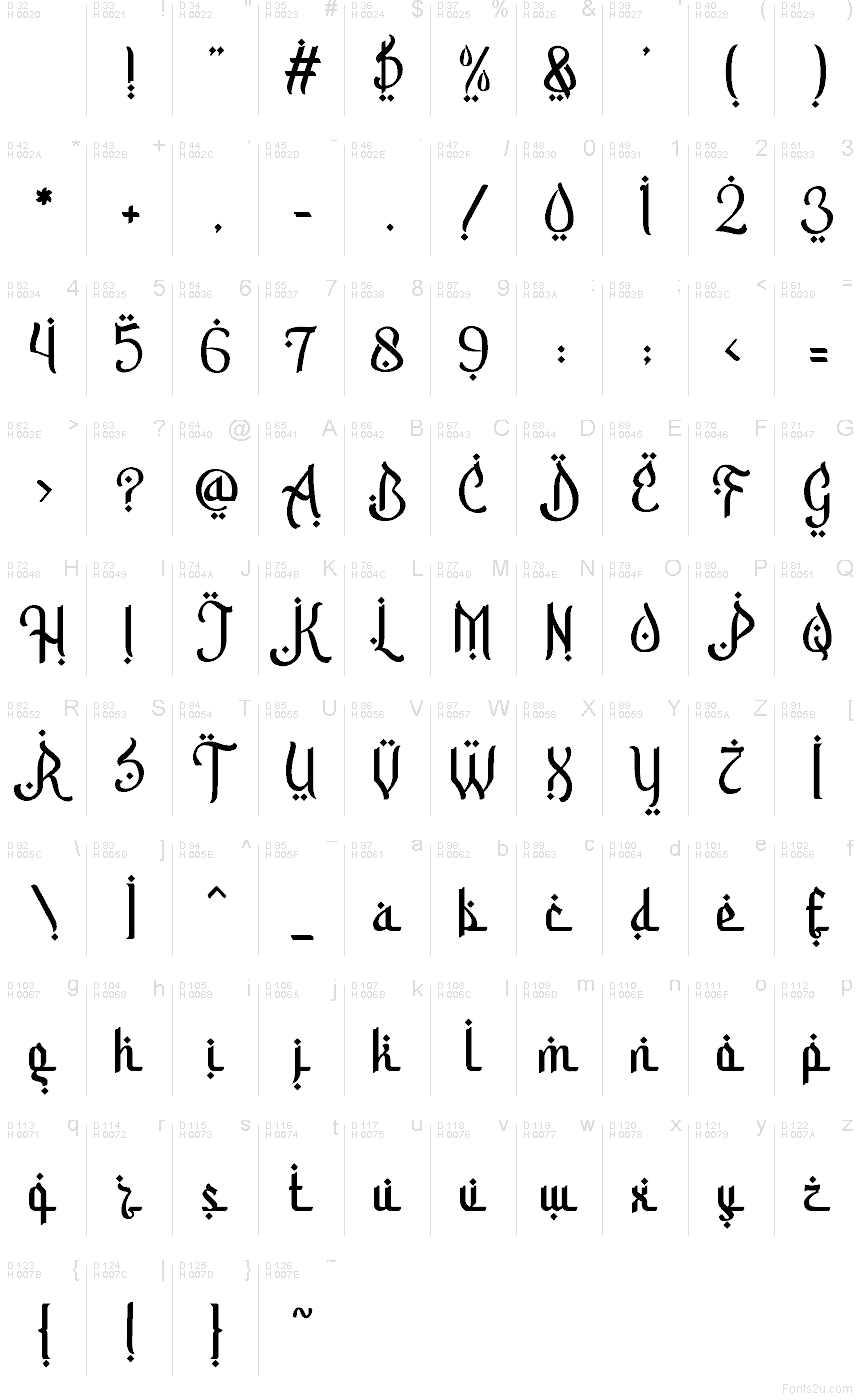
Majidi Mirage Three
Majidi Mirage Three od Putracetol Studio je arabské display písmo, ktoré tvoria vysoké vertikálne ťahy, ostré krivky a pravidelný vzor diamantových bodiek – tie pôsobia ako súčasť konštrukcie, nie ako dekorácia. Tento rytmus dodáva písmenám slávnostný, kaligrafický nádych, zatiaľ čo široké spodné krivky udržiavajú celkový vzhľad pevne na zemi.
Plagáty, titulky, obaly kníh, branding a grafika pre podujatia môžu využiť túto siluetu s vysokým kontrastom na to, aby krátkym textom dodali autoritu. Písmo sa hodí aj pre identitu reštaurácií či materiály ku kultúrnym festivalom, kde zašpicatené bodky a zdvihnuté oblúky dodávajú nadpisom nezameniteľný arabský charakter bez potreby ďalších ozdôb.